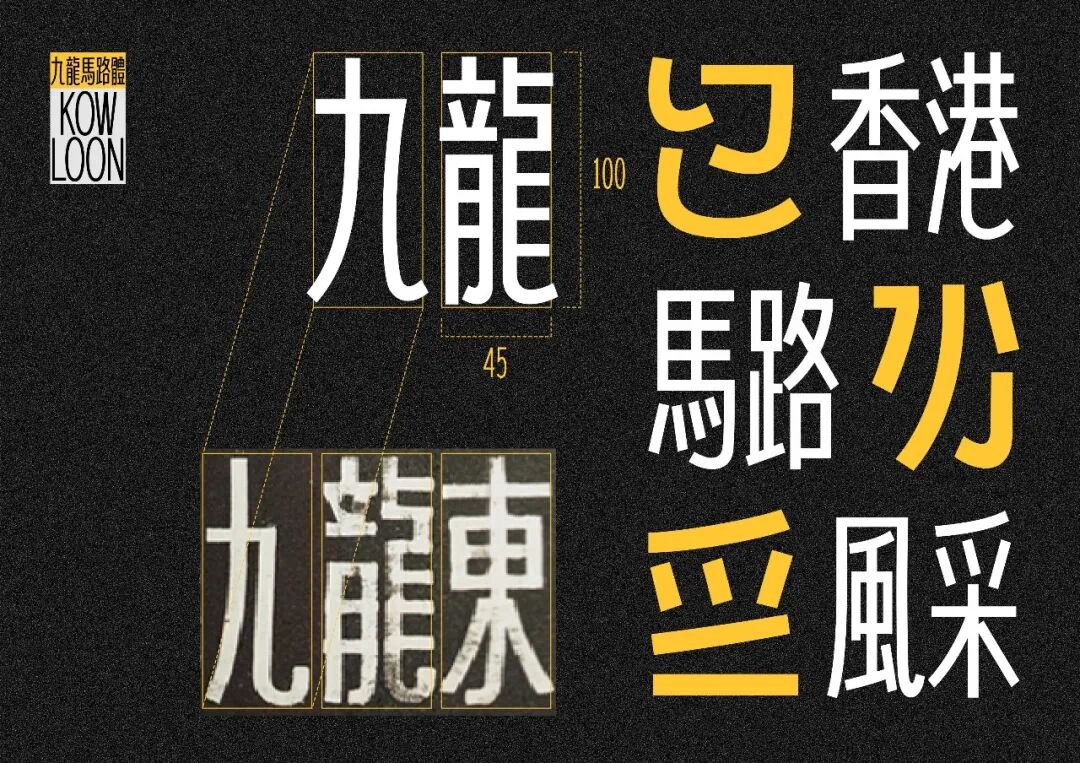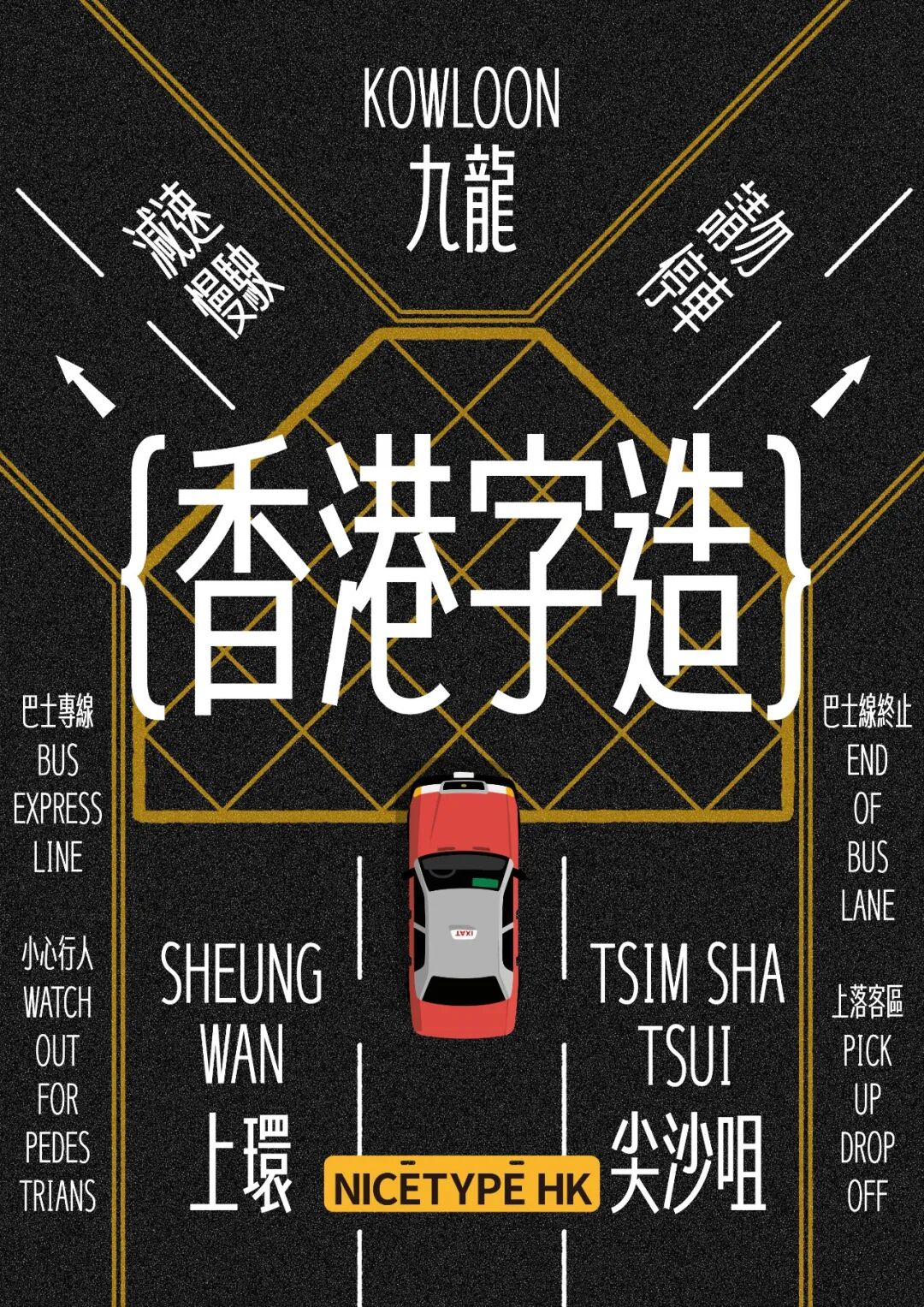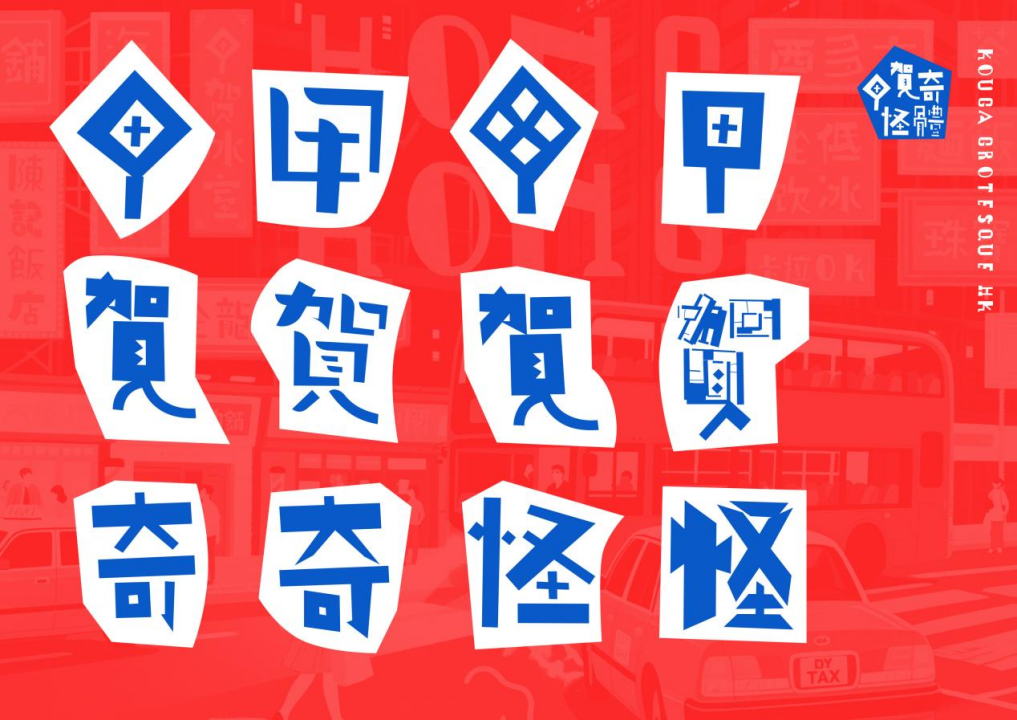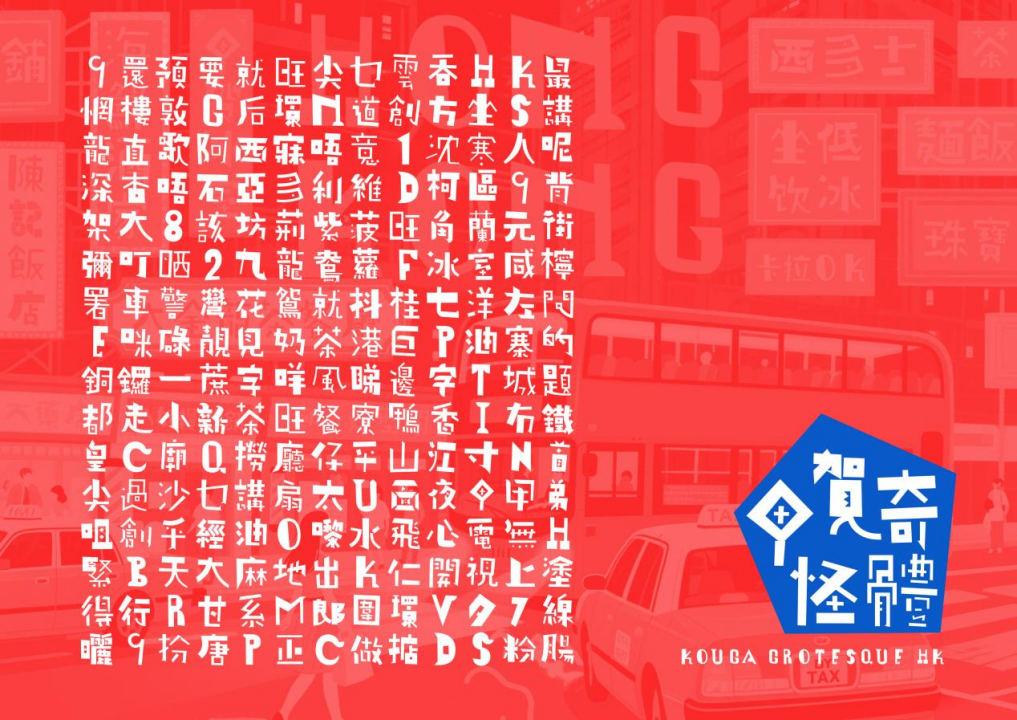
喜报|NICETYPE HK 入选 2025 年「香港・創 + 造」品牌嘉許计划,以“香港字造”镌刻城市文化记忆
各位朋友,有好消息同大家報喜啦~2025年「香港・創 + 造」品牌嘉許計劃嘅入選名單終於出爐!NICETYPE HK 成功攞到呢個殊榮,真係值得開心!
NICETYPE HK榮獲由香港科技創新促進組頒發的「香港•創+造」品牌嘉許獎項,並於「設計」範疇中脱穎而出,獲得專業評審團的肯定!再次向大家證明,「香港字造」同「香港品牌」係幾咁有魅力!
「香港・創 + 造」品牌嘉許計劃自推出以嚟,一直以重塑「香港製造」同「香港品牌」嘅卓越聲譽為目標,專注表彰一班喺創新領域堅持耕耘、為行業升級帶嚟新動力嘅優秀企業。呢個計劃唔單止係對品牌實力嘅認可,更係推動香港創科發展嘅一大助力,為本地品牌搭建一個好重要嘅展示平台,齊齊交流、互相提升。
香港字造,世界共賞
NICETYPE HK 秉承「香港字造」嘅精神理念,透過字體設計,連繫香港嘅過去、而家同未來,等文字成為展現香港文化魅力嘅窗口。佢哋持續用字體去演繹香港獨特嘅語言特色同城市精神,呼應「香港製造」對品質同本土特色嘅堅持,亦為「香港品牌」注入咗文化厚度同獨特辨識度。
品牌團隊一直好用心咁深入探索香港嘅語言文化同視覺美學,細心挖掘歷史入面好多珍貴嘅符號,將香港獨有嘅地標意象、有趣嘅方言節奏,甚至係充滿質感嘅建築紋理,巧妙拆解再融入字體設計嘅細節之中。每一款字體嘅誕生,都係對香港文化基因嘅精准解讀,同時都係對城市精神嘅生動演繹。
NICETYPE HK致力以字體為媒介,為各式IP注入生命力。喺佢哋手下,每個字都唔再係冰冷符號,而係載住香港街角故事同集體回憶嘅視覺片段。透過「香港字造」,品牌成功建立起一條連接香港過去、現在同未來嘅文化橋樑,等更多人可以透過文字感受呢座城市嘅獨特魅力。
今次入選「香港・創 + 造」品牌嘉許計劃,係對NICETYPE HK喺文化創新同品牌建設路上努力嘅高度認可。期待NICETYPE HK繼續以字體做筆、以文化做墨,傳承香港優秀文化之餘不斷創新,為「香港字造」同「香港品牌」寫下更輝煌嘅一頁,令我哋的城市文化記憶喺文字世界裏面永久流傳落去。